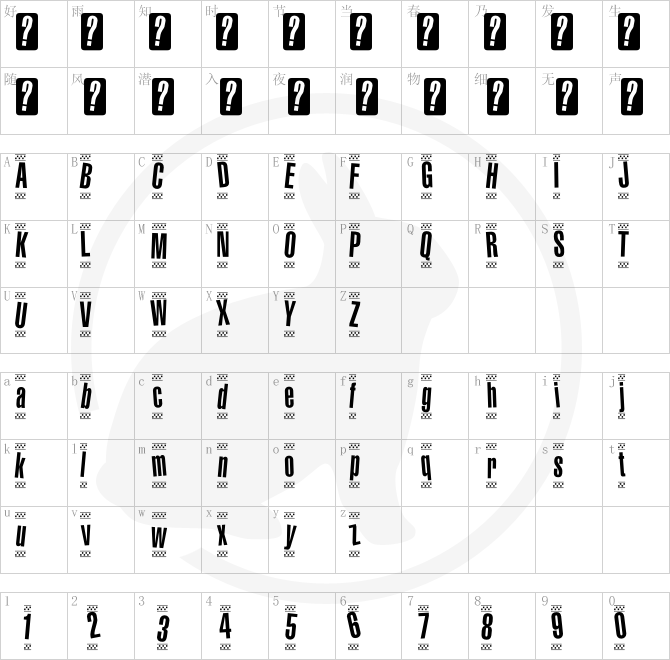
Nineteen Eighty Portable.otf字体下载,这款字体结构工整、笔画清晰,兼顾美观与易读性,适用于标题、正文、海报、包装、LOGO 等多种场景。字形优雅稳定,风格百搭耐看,适配日常排版与创意设计,让文字呈现更舒适、更具质感。Nineteen Eighty Portable.otf字体下载一笔一画,皆是细节,以均衡的比例、流畅的线条打造舒适视觉体验,字形端正大气,风格简约现代。无论是商业设计、品牌宣传还是日常排版,都能轻松驾驭,让文字更有格调与力量。Nineteen Eighty Portable.otf字体下载字体下载。